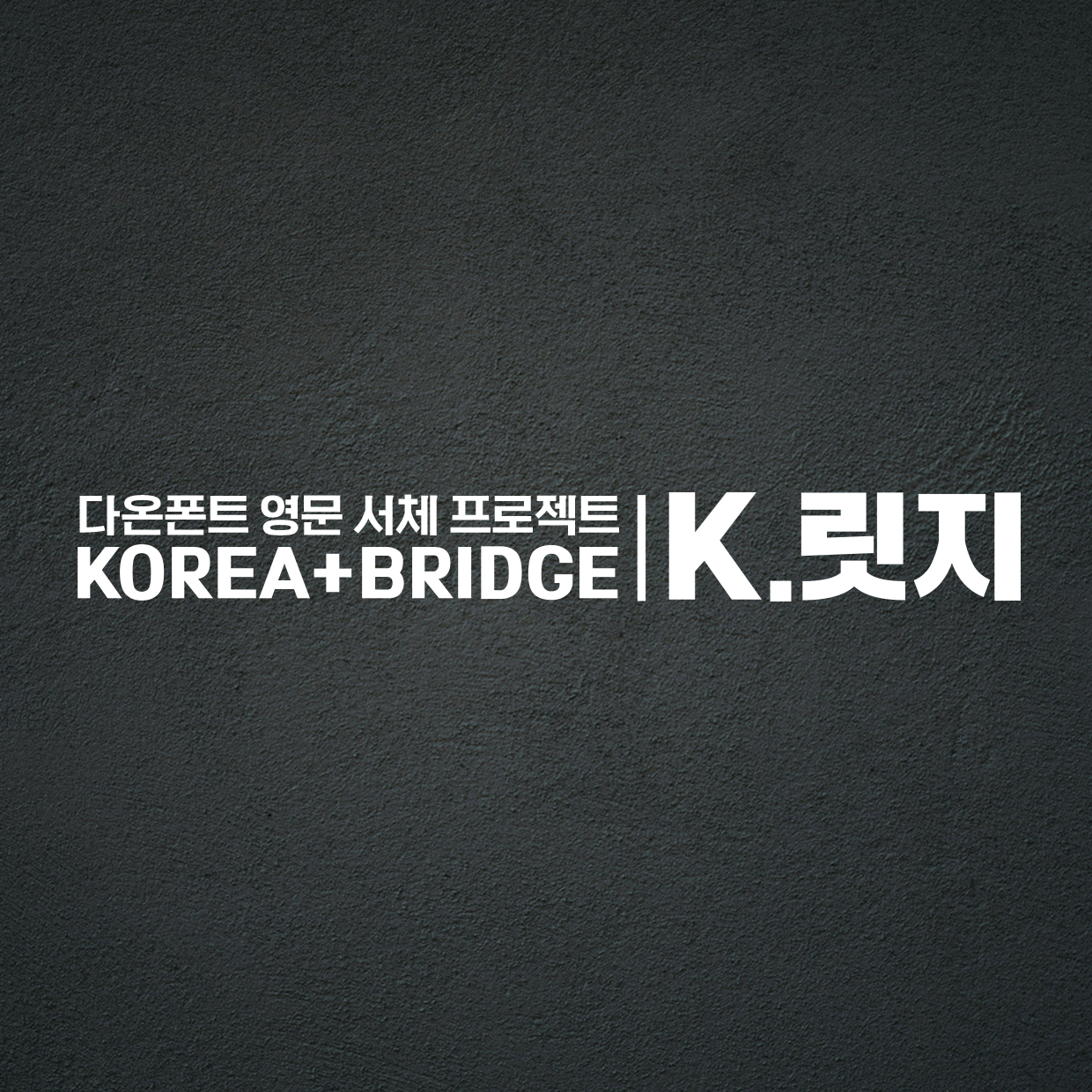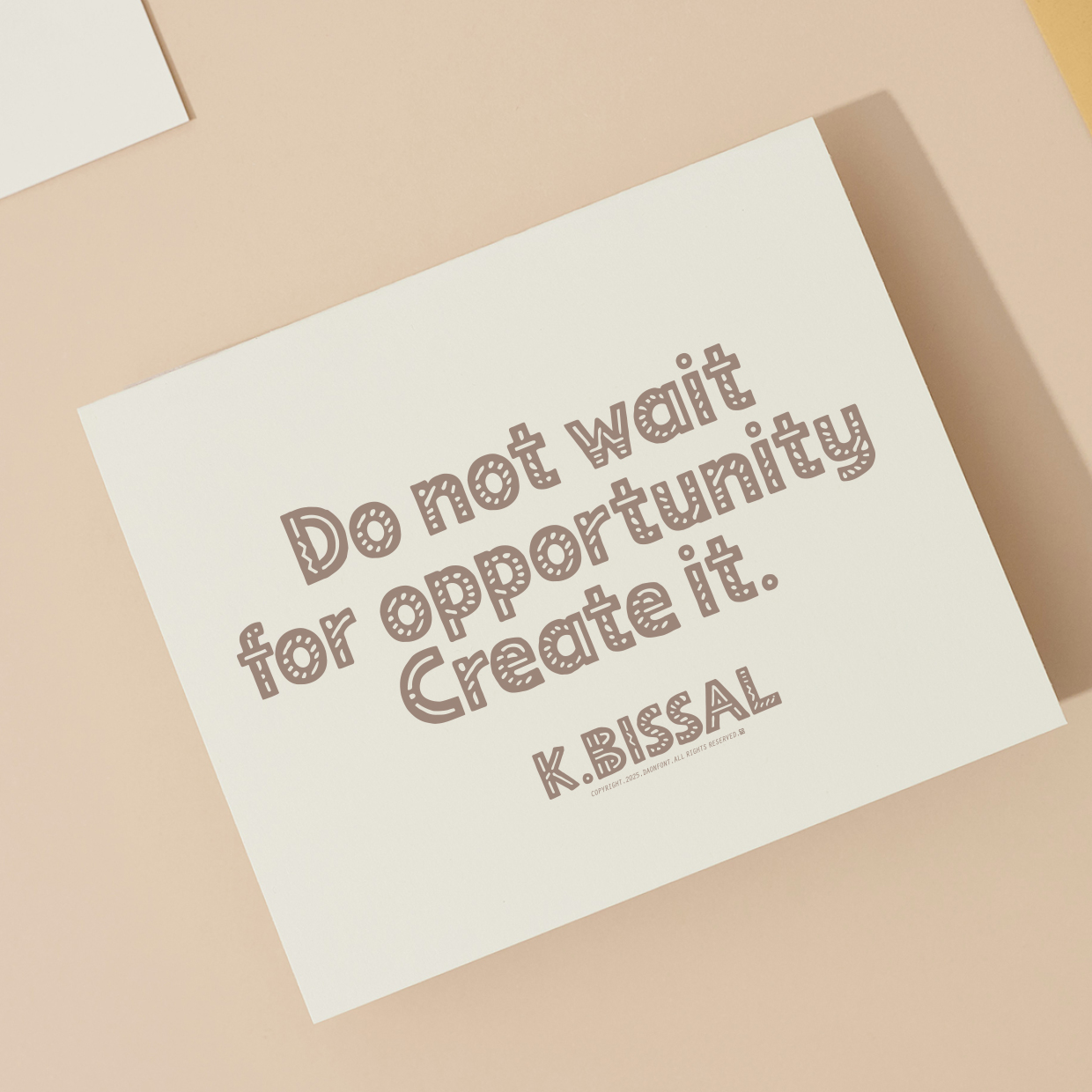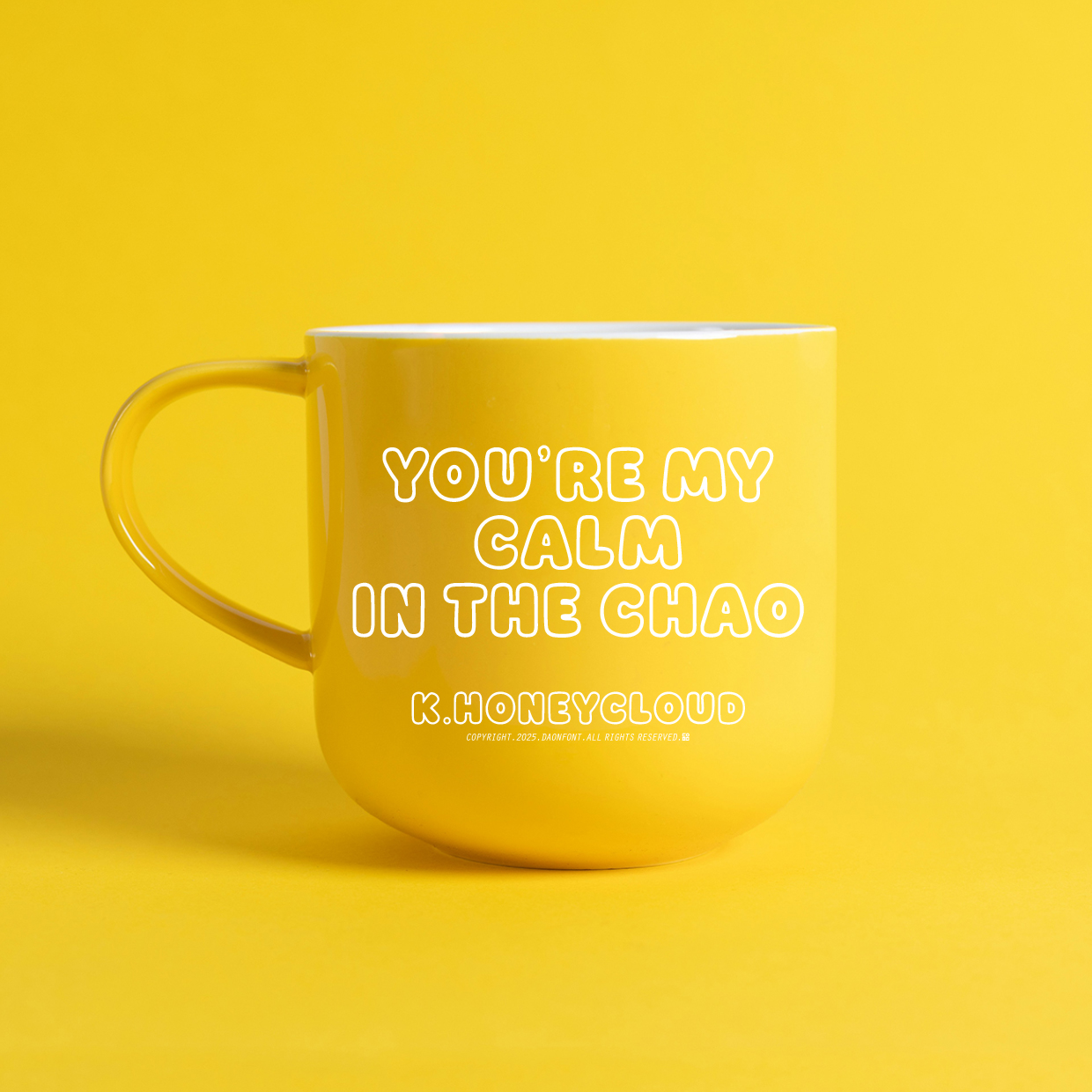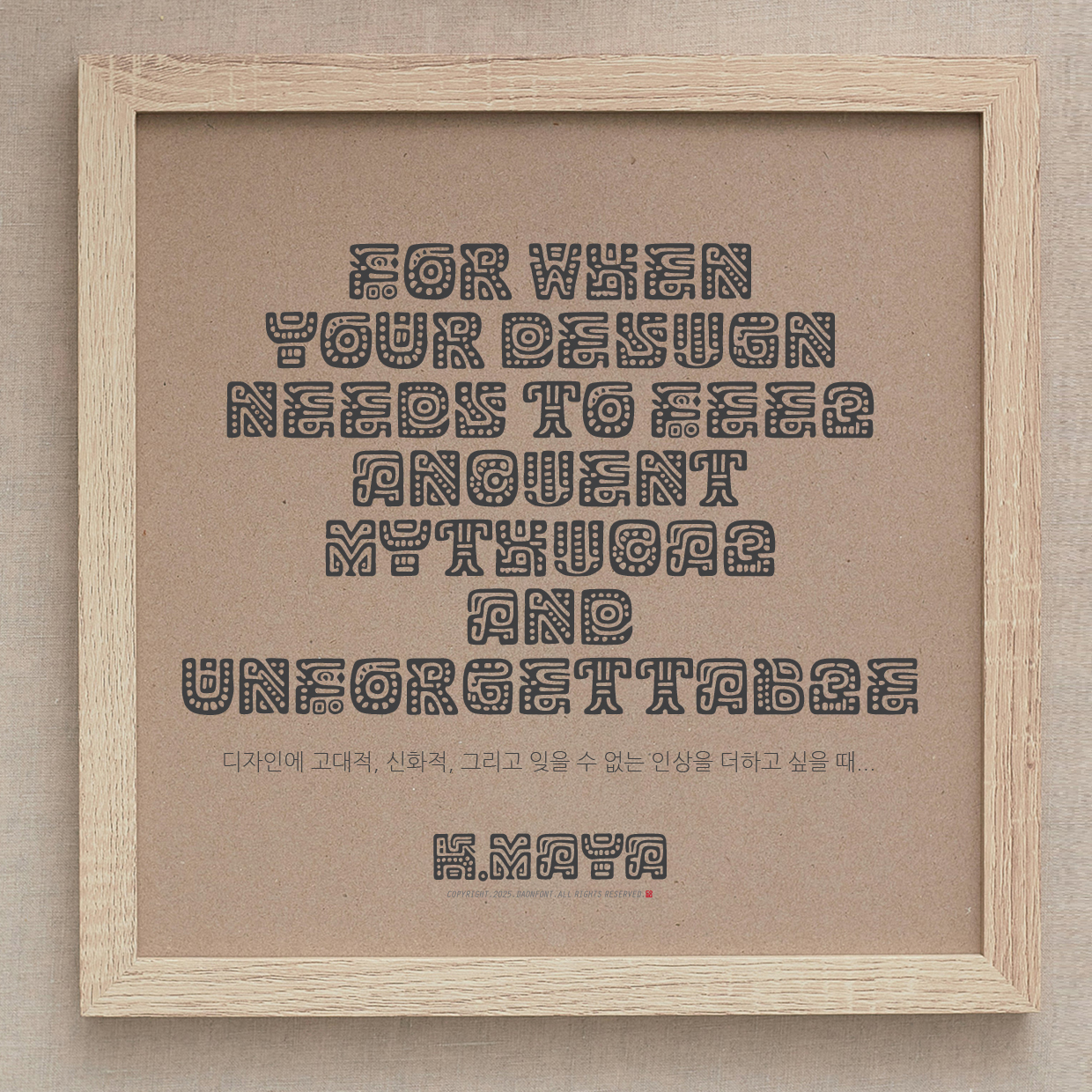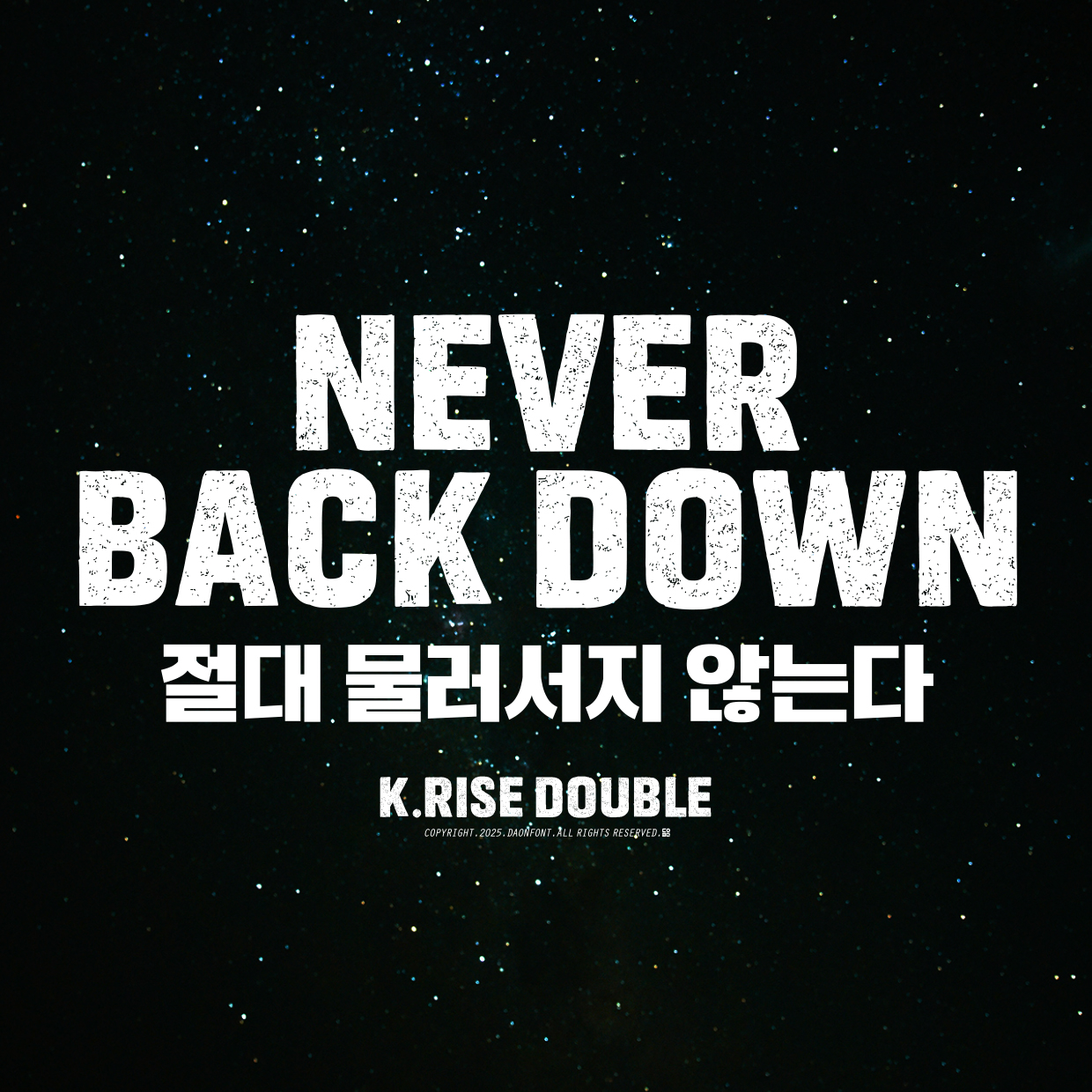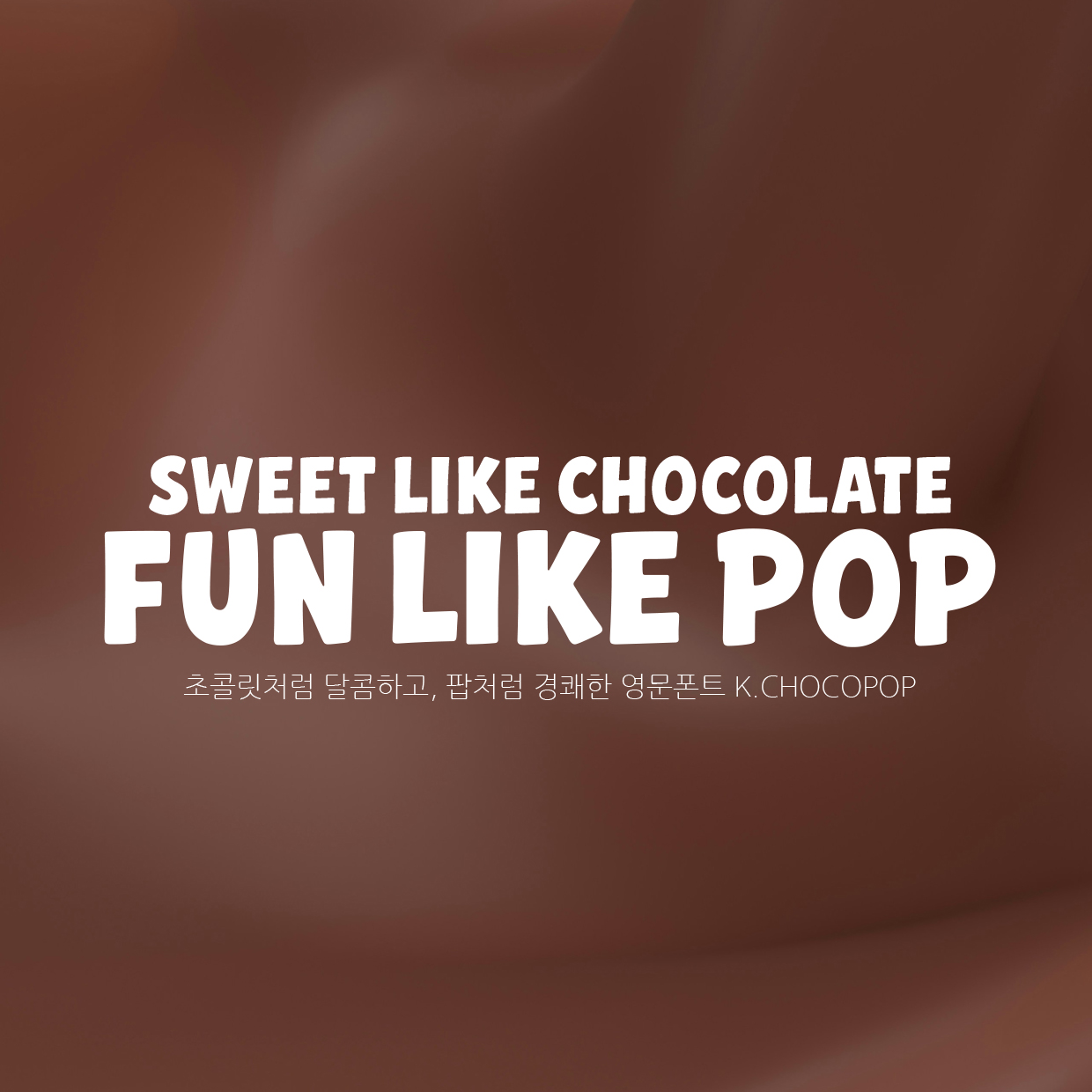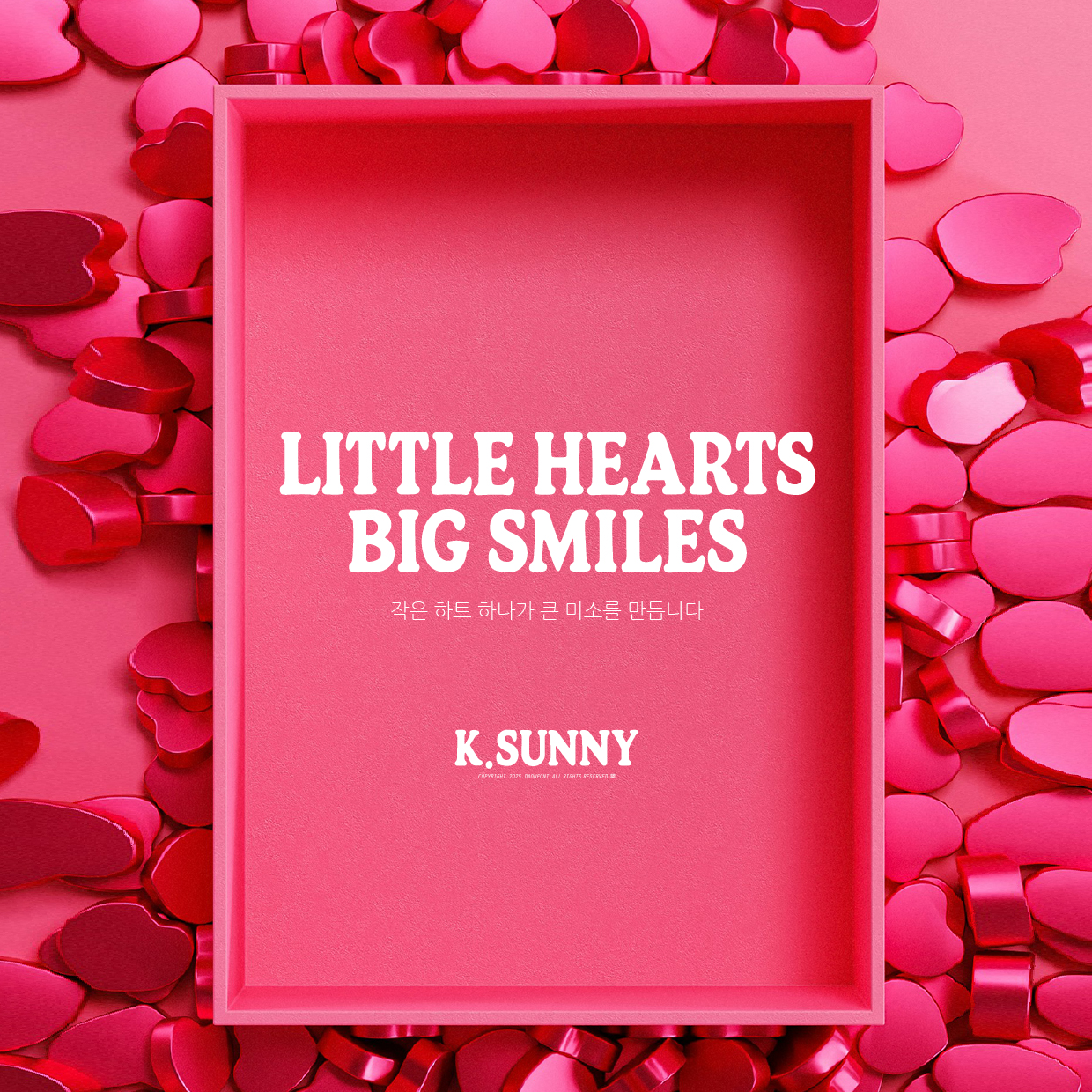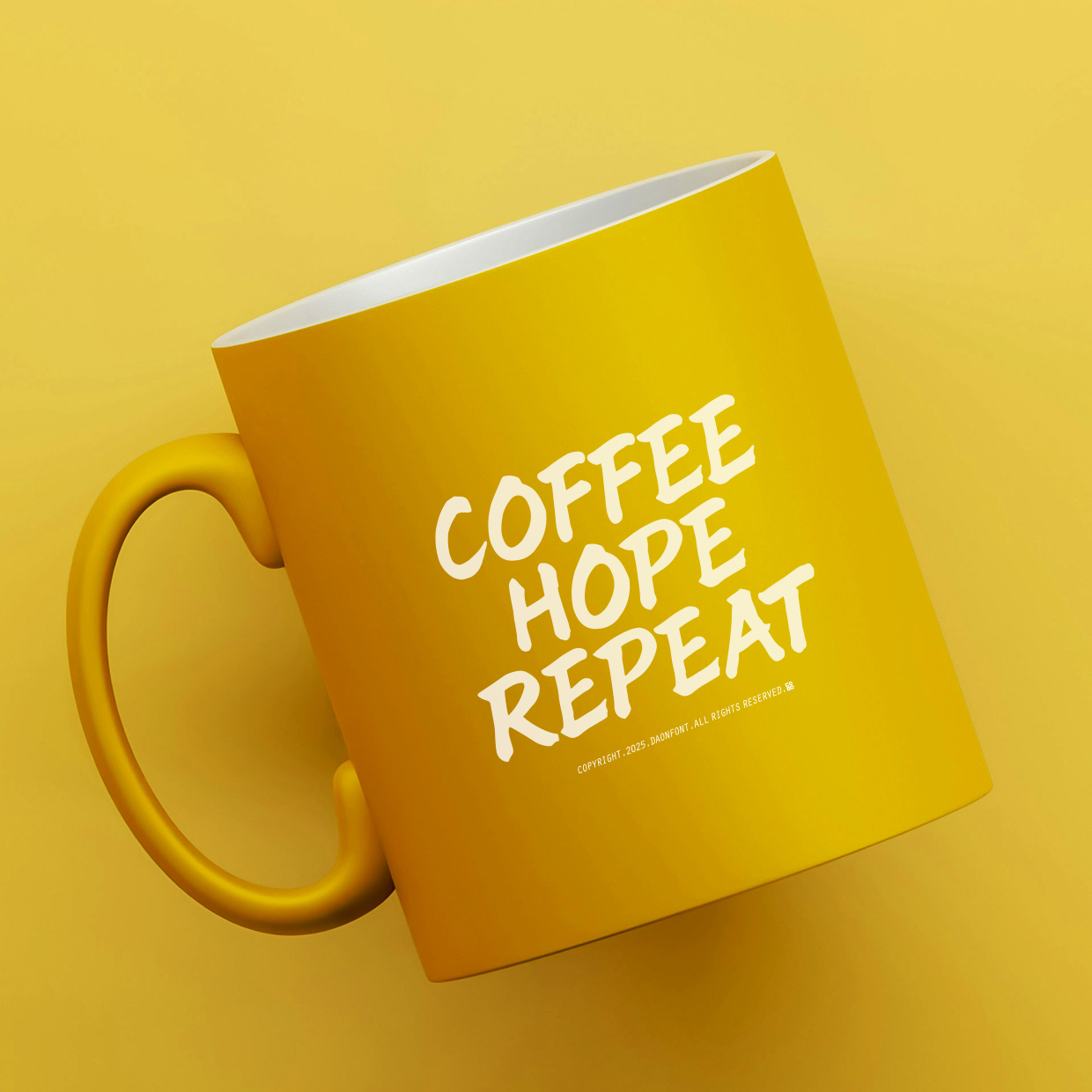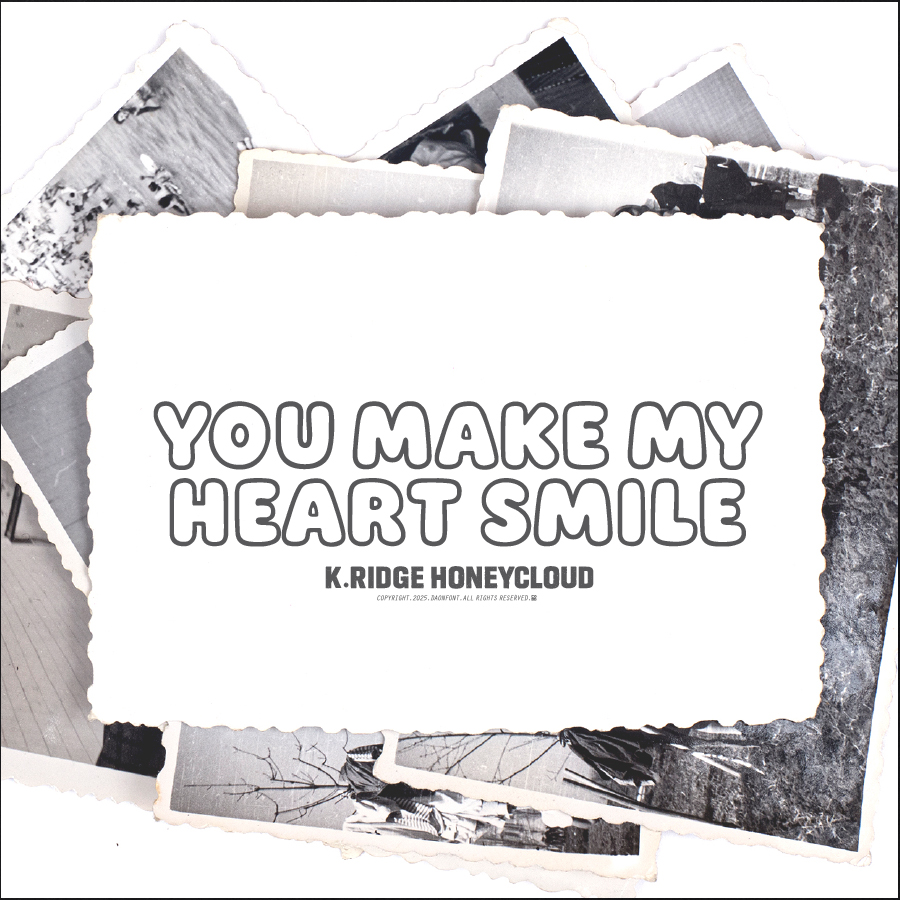
K릿지 프로젝트 1차 영문폰트 11종 업데이트 안내
다온폰트의 K릿지 프로젝트 1차, 프리미엄 영문폰트 11종이
홈페이지에 새롭게 업데이트되었습니다.
브랜딩, 타이틀, 아트웍에 최적화된 감각적인 서체들을 지금 만나보세요.
트렌드와 감성을 담은 K릿지 프로젝트의 첫 번째 라인업을 다온폰트에서 확인해보세요.